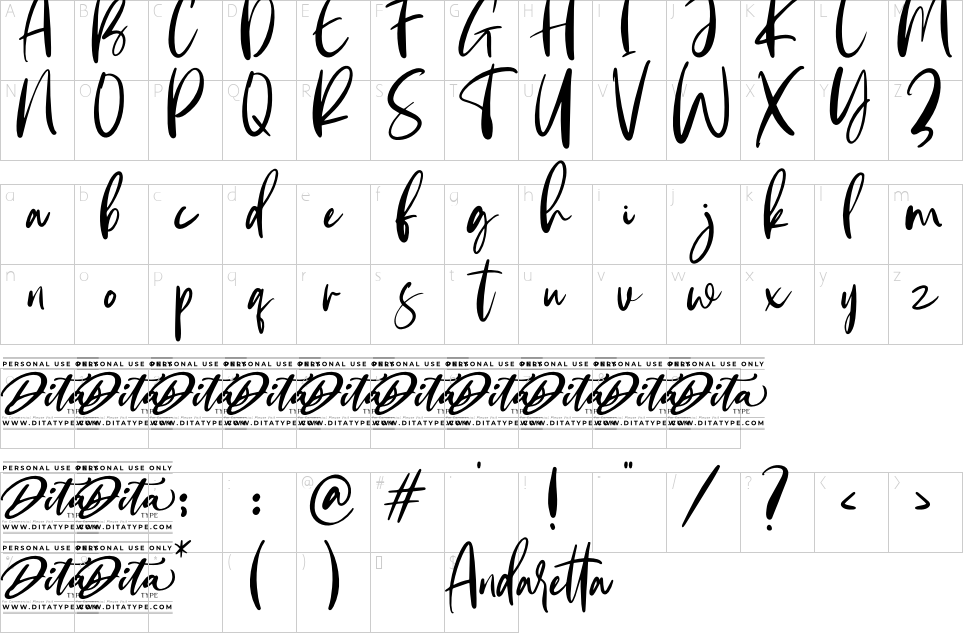
Andaretta é uma fonte moderna e elegante, criada pela Dita Type. Seu design suave e fácil de ler torna-a perfeita para uso em websites, revistas ou qualquer outro projeto gráfico que valoriza a simplicidade. Ela foi desenvolvida com uma paleta de cores sofisticada que combina perfeitamente com muitos estilos de design. Foi baixada 2,269 vezes, demonstrando sua popularidade entre designers e criadores de conteúdo. Seja você um designer de moda, um criador de sites ou um editor de revistas, Andaretta pode ser a escolha perfeita para adicionar um toque de sofisticação a seus trabalhos. Instale e descubra por si mesmo o poder de Andaretta.